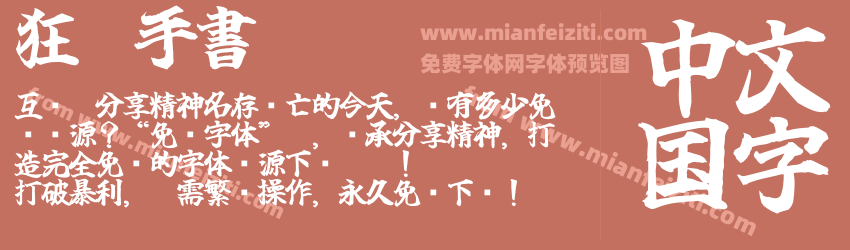
狂霸手书是一款非常有气势的手写字体,日语名玉ねぎ楷書「激」無料版,免费字体网为方便大家,命名为狂霸手书!
◇概要◇
设想动画、同人志、贺年卡等所有创作场景而制作的简单手写毛笔字体洋葱楷书(ttf形式)稍微有些激烈。
这个字体是免费版(JIS第一水准汉字+)α)是的。
*现在正在制作JIS第二水准对应版。(我想做成布施风格)
【收录文字】
全角345字(平假名、片假名、012、ABC、abc、希腊文字、俄罗斯文字)
符号233个字(?〆株式会社{}@@@@@@@@@@@@@@@@@@@@@@@@@@@@@@@@@)
半角157字
JIS第一水准汉字全2965字
独断选择的创作中使用的汉字约几十个字